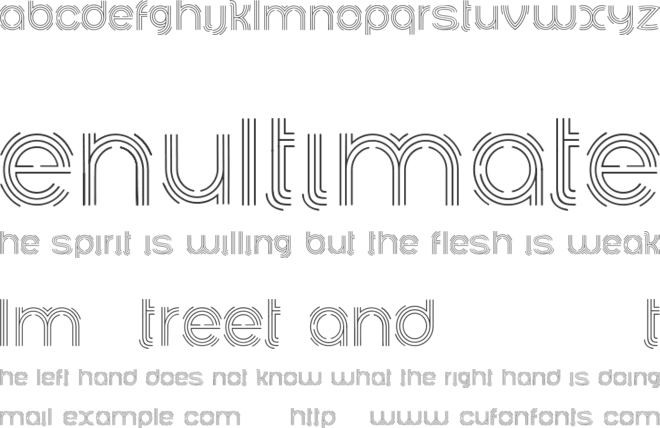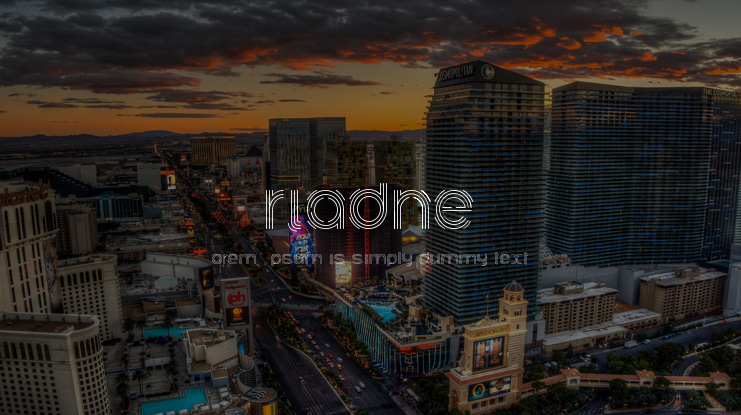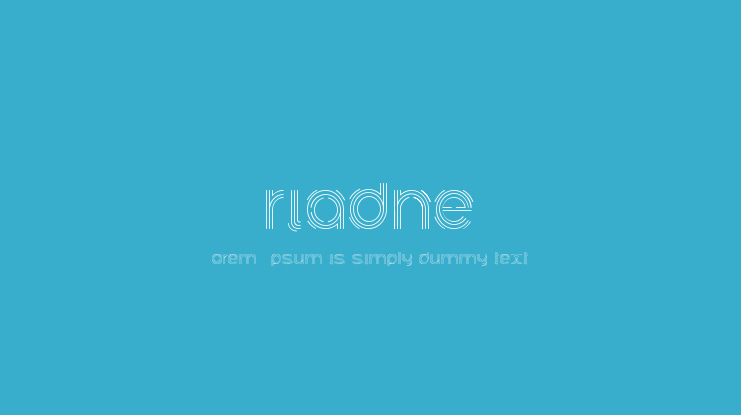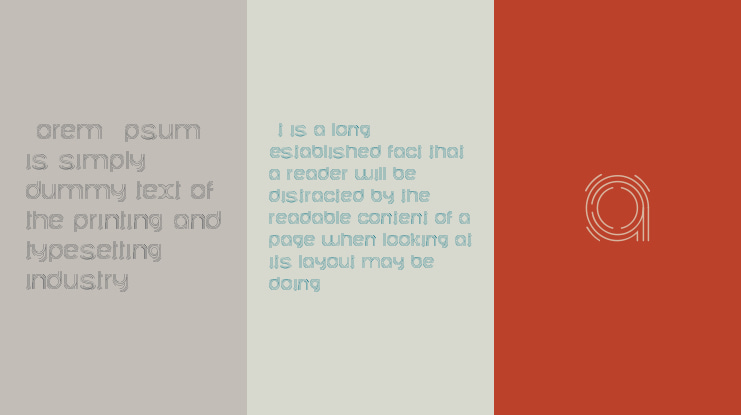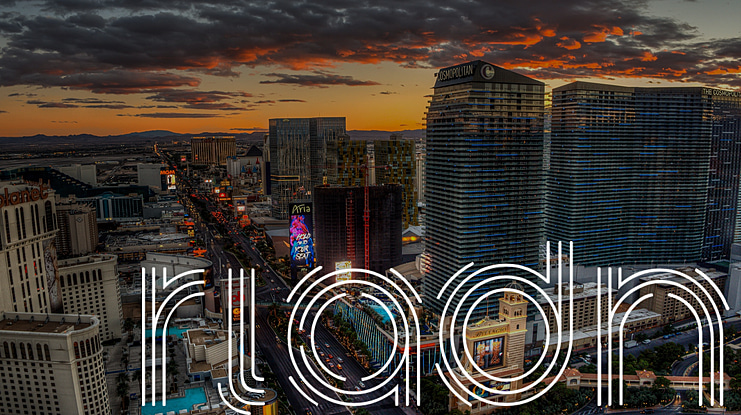
Ariadne Font
Arthur Tavares, Marcos Mourão, Camilla Paiva, Júnior Chav...
A Ariadne BR explora o conceito de labirinto. A ideia é explorar a ideia de um conjunto de caminhos feitos de modo a confundir quem o percorre, criando uma fonte relativamente condensada, com curvas concêntricas e que explora bastante a sinuosidade de suas formas.